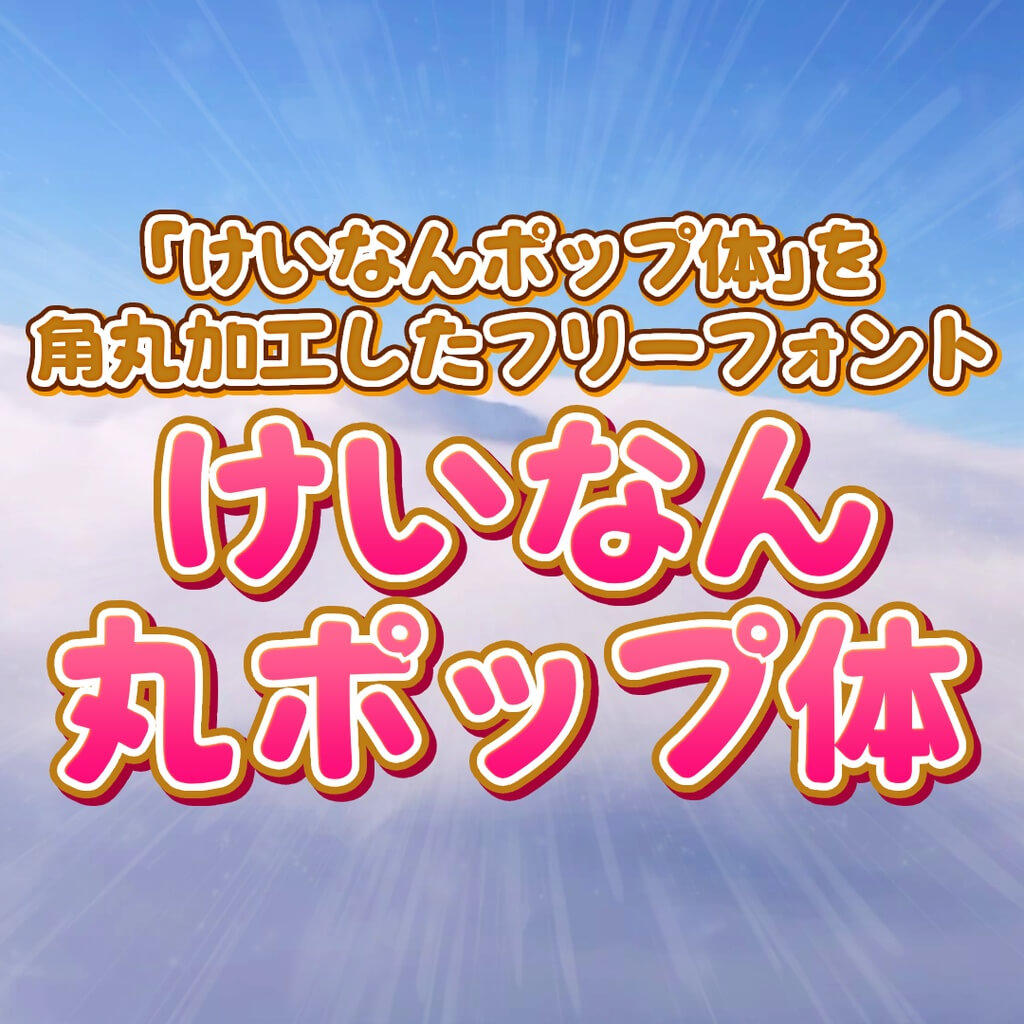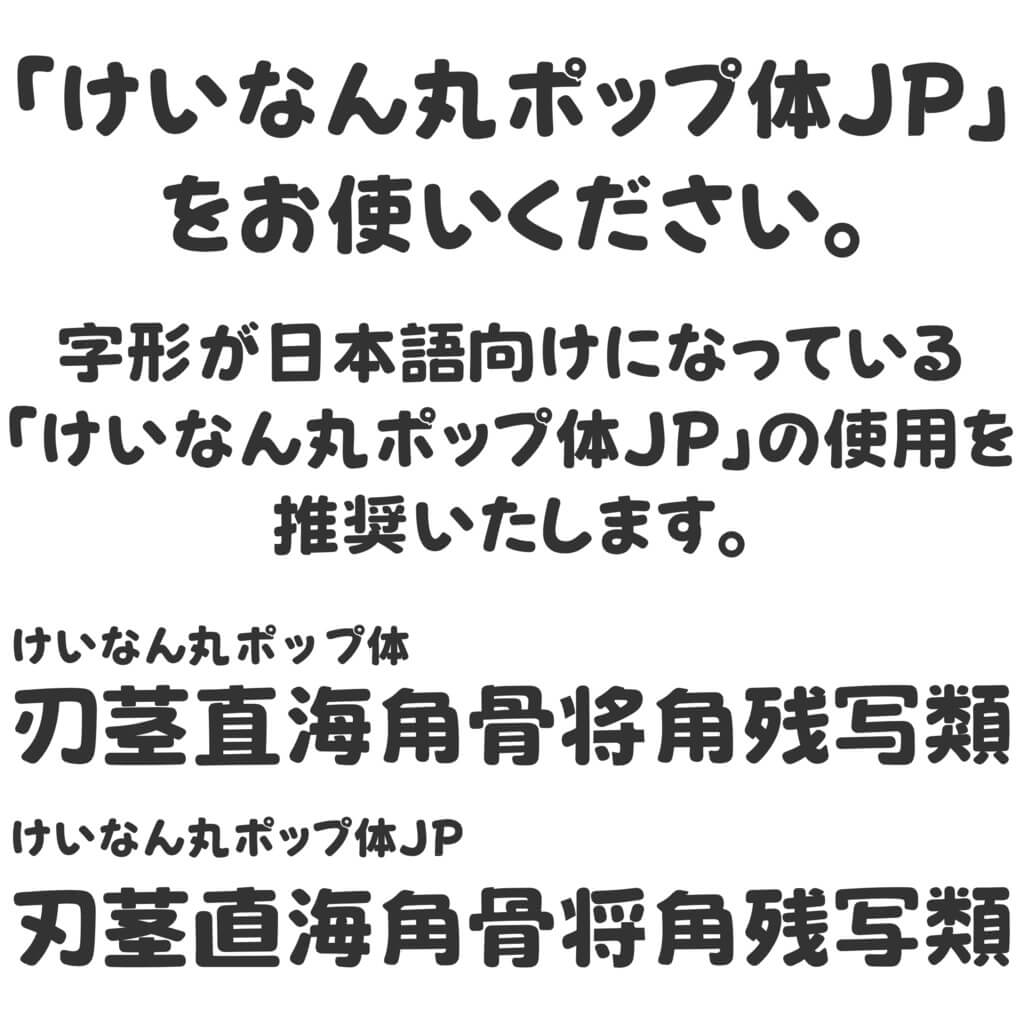
荆南圆体けいなん丸ポップ体
けいなん丸ポップ体(中译:荆南圆体) 是一款以 “源暎ぽっぷる” 与 “荆南波波黑” 混排的 “けいなんポップ体(中译:荆南POP体)” 为基础,经由栃木那须的 Yuzunoka 先生(或女士)根据日文字形进行优化调整,形成 “けいなんポップ体(中译:荆南POP体)” 后,再进行圆角加工而成的免费商用字体。该字体风格活泼醒目,适用于广告、海报、标题等多种场景,能够为你的设计增添独特的视觉效果。